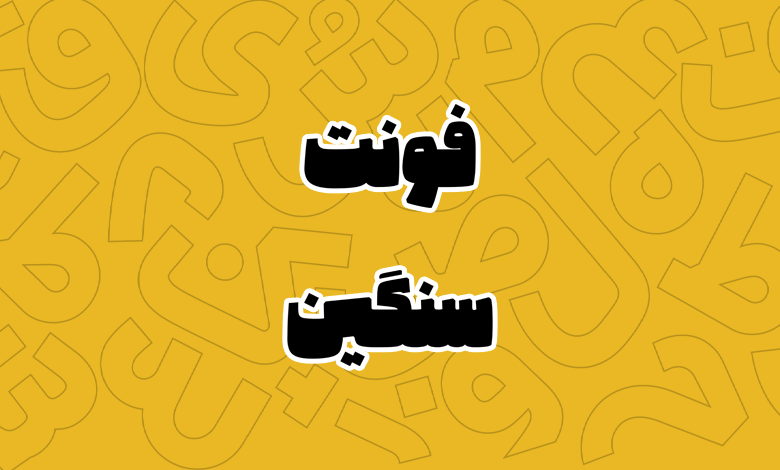
فونت سنگین (Sangin)
فونت سنگین (به انگلیسی: Sangin) از سری فونتهای نسخ مناسب برای عناوین، تبلیغات و تیترنویسی است که مشابه نامش ساختاری فوقسنگین دارد. این فونت با پشتیبانی از ۴ وزن و ۵ سبک نقطهگذاری است، مجموعا ۲۰ استایل را شامل میشود. علاوهبر این دارای نسخه وریبل با متغیر وزن و تغییر شکل نقطه است.
احد هاشم زاده این فونت را با هدف پر کردن خلا فونتهای سنگین طراحی کرده است. به عقیده وی اغلب فونتهای فوقسنگین که برای استفاده در تیترها، بستهبندی محصولات و عناوین استفاده میشوند، تکوزن بوده و آنطور که باید نیازهای ما را برطرف نمیکنند. از طرفی دیگر تجربه چندساله وی در زمینه طراح گرافیک برای بستهبندی محصولات سبب شد تا در جهت رفع این نیاز فونت سنگین را خلق کند.
این فونت به منظور نمایشیتر کردن حروف و کلمات از ساختار ترکیبات جایگزین نیز بهره میبرد. بهطوریکه میتوانید ترکیبات و حروفی مانند «ـک، ـهـ، ـد، ـی، ـنی، صـ، ـتـ، ـر» را با ظاهری متفاوت تایپ کنید تا ساختار کلمات شما متنوعتر شده و نگاه مخاطبان را به خود جذب کند.
یکی دیگر از ویژگیهای این فونت سنگین پشتیبانی از زبانهای مختلف است که آن را برای ما کاربران ایرانی مناسب میکند. علاوه بر زبان فارسی، زبانهایی همچون انگلیسی، عربی، کردی و اردو نیز در این فونت پشتیبانی شده است. پشتیبانی زبانها از نظر اعراب، کاراکترهای خاص و اعداد کاملا استاندارد است. در ادامه تصاویری از این فونت را در کاربردهای متنوع مشاهده میکنید.